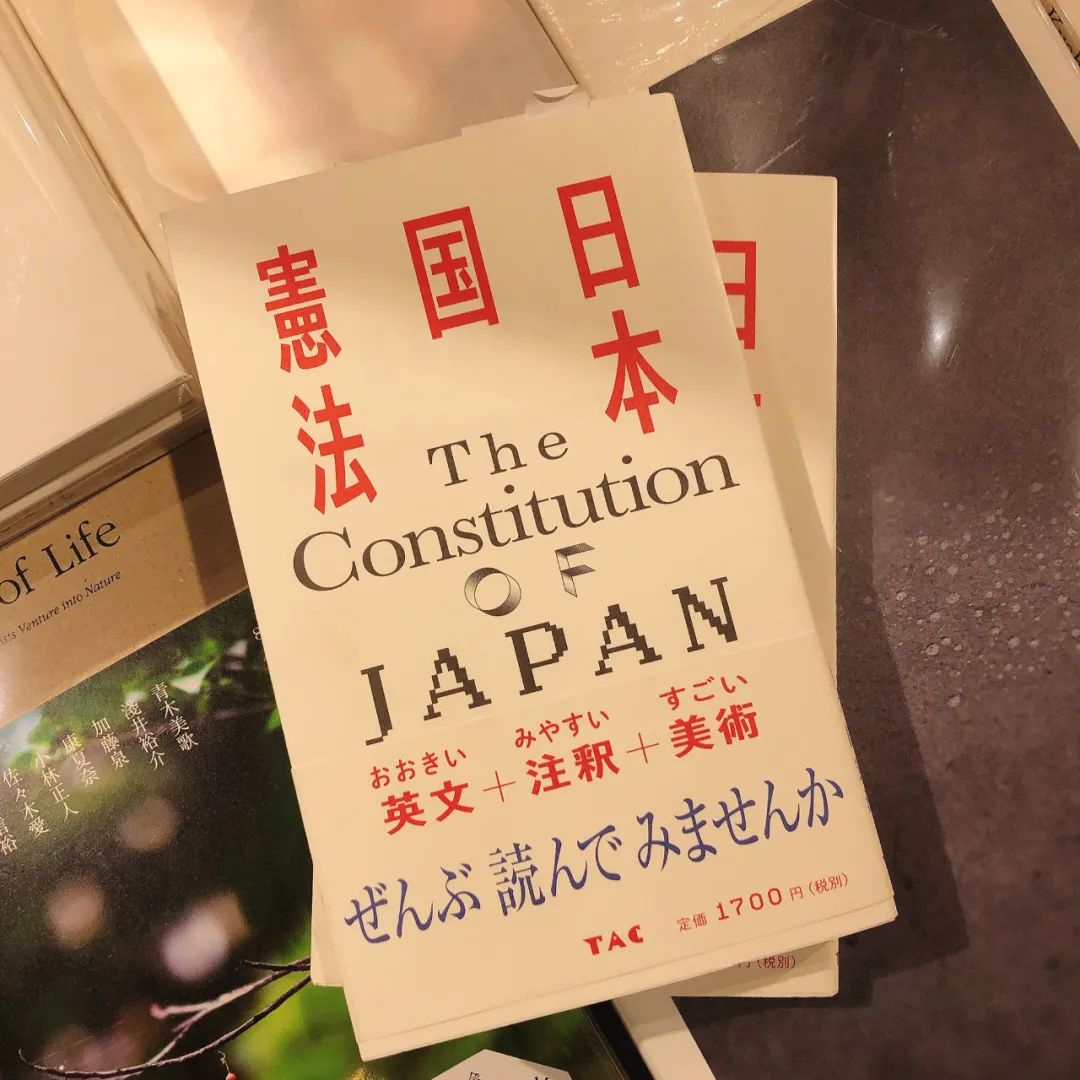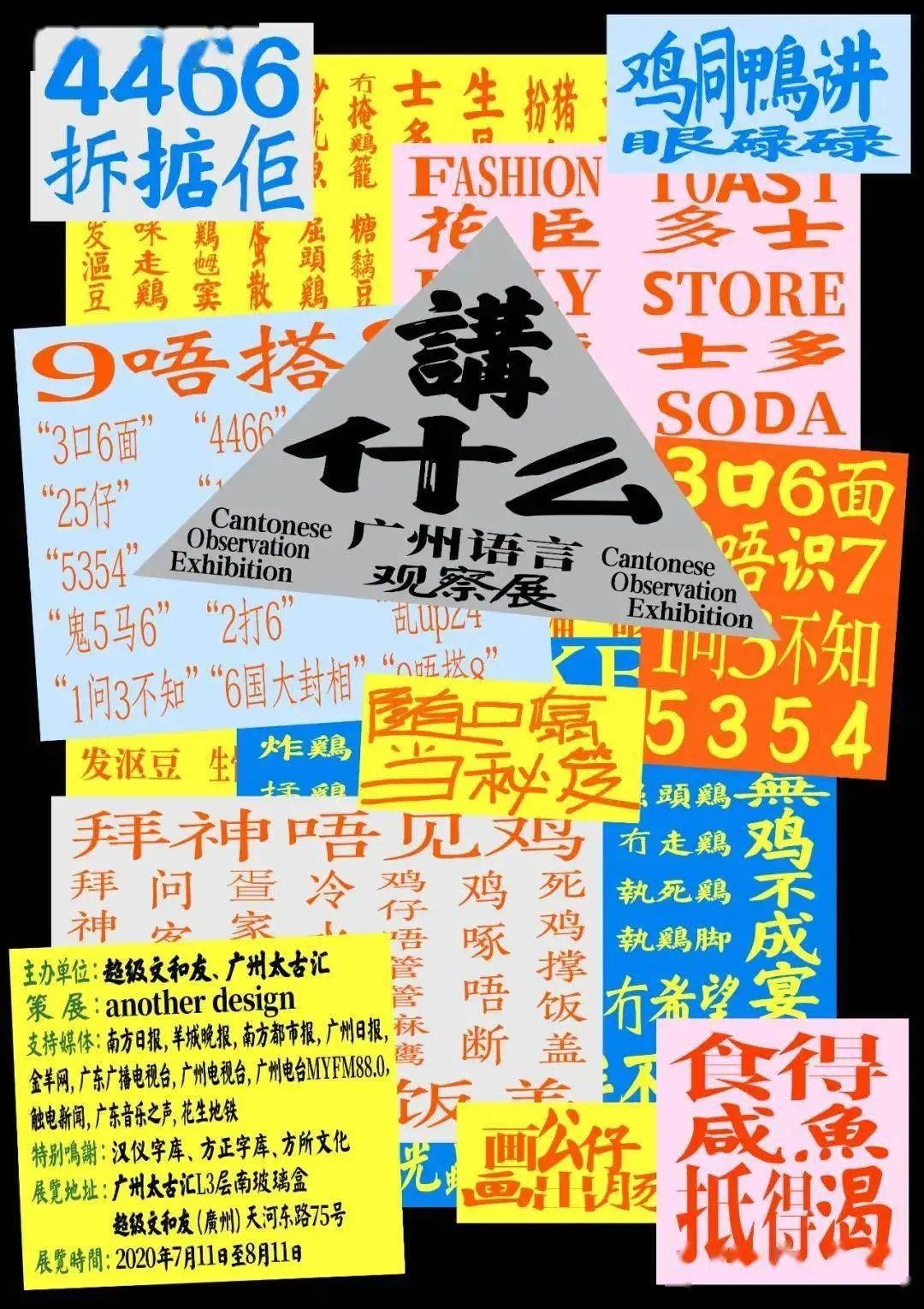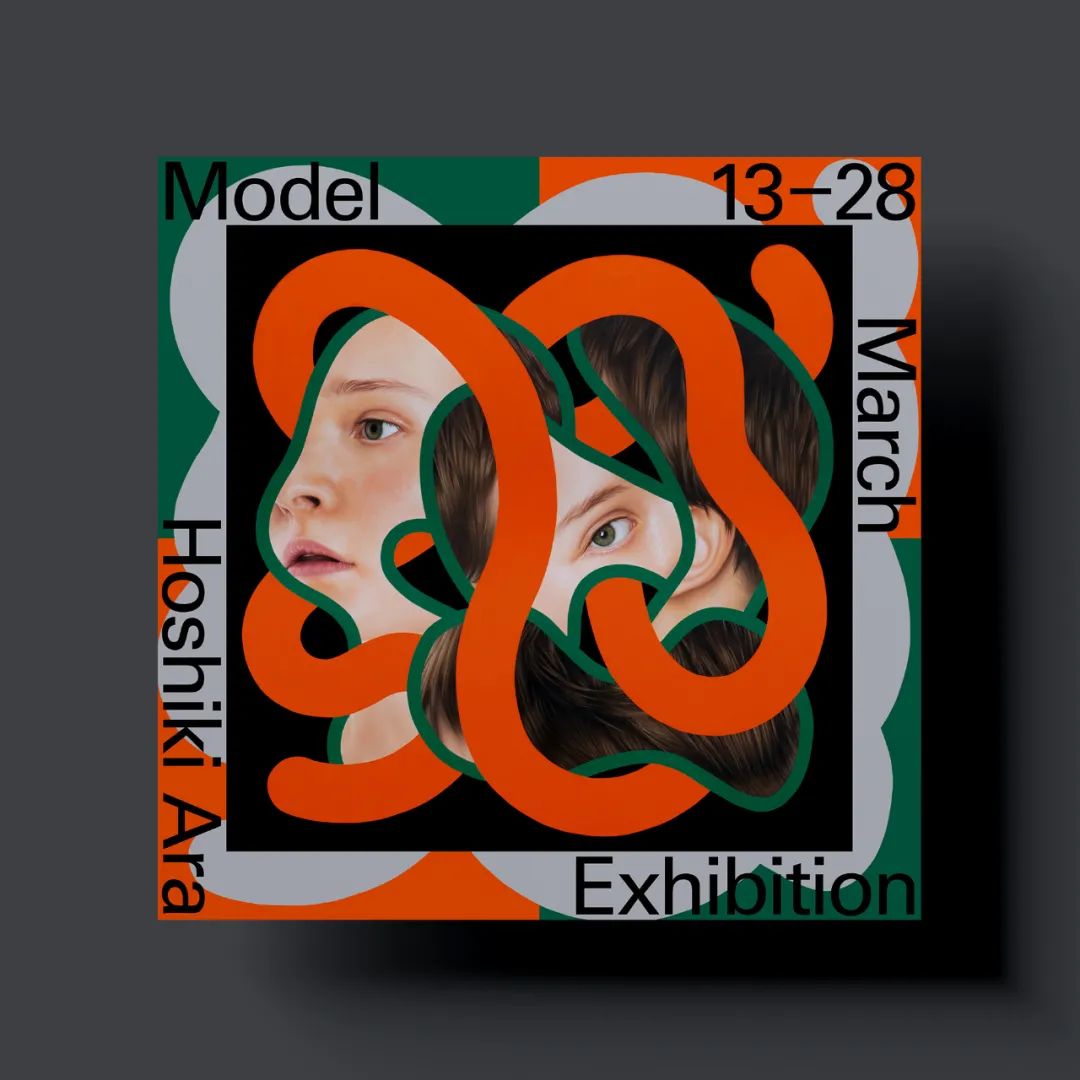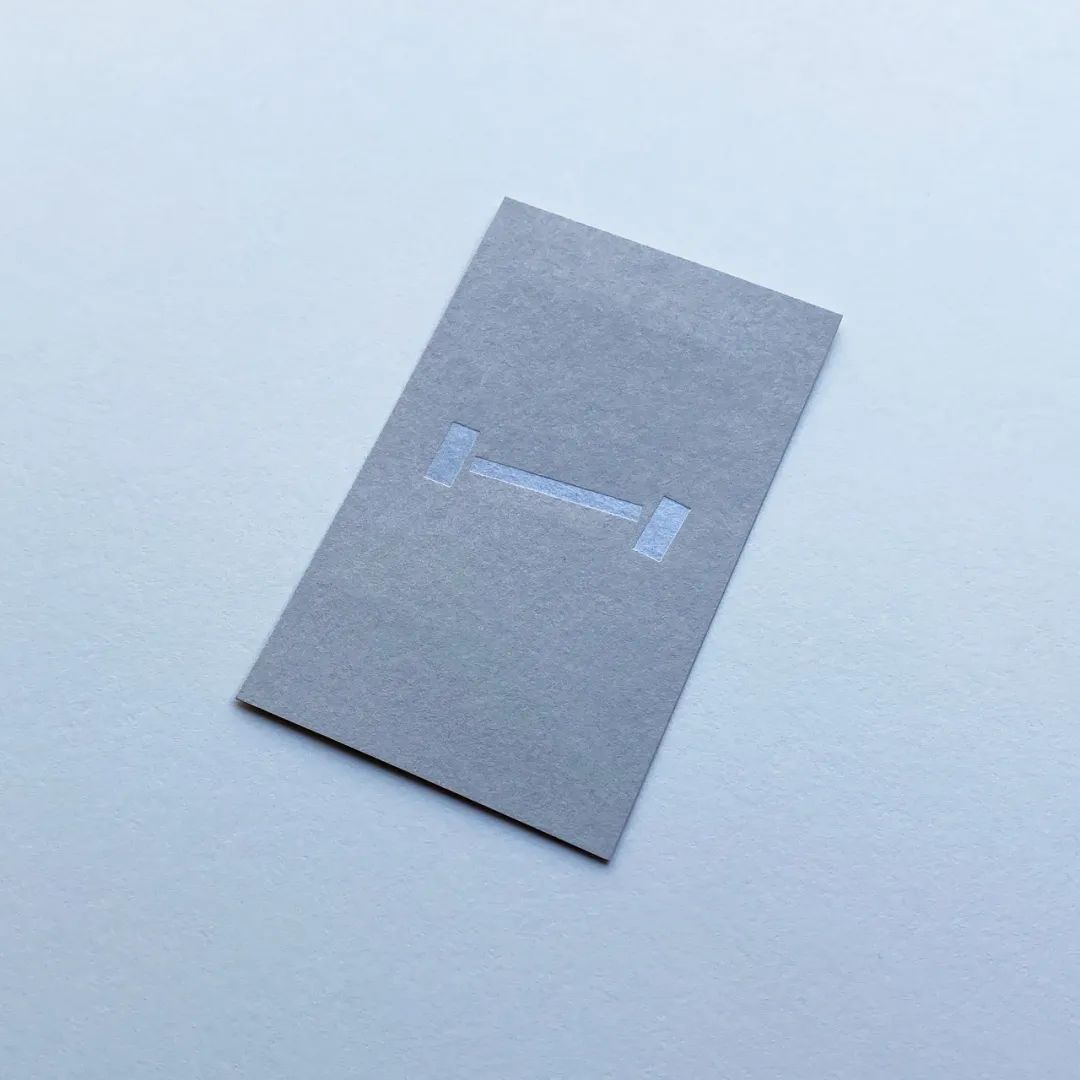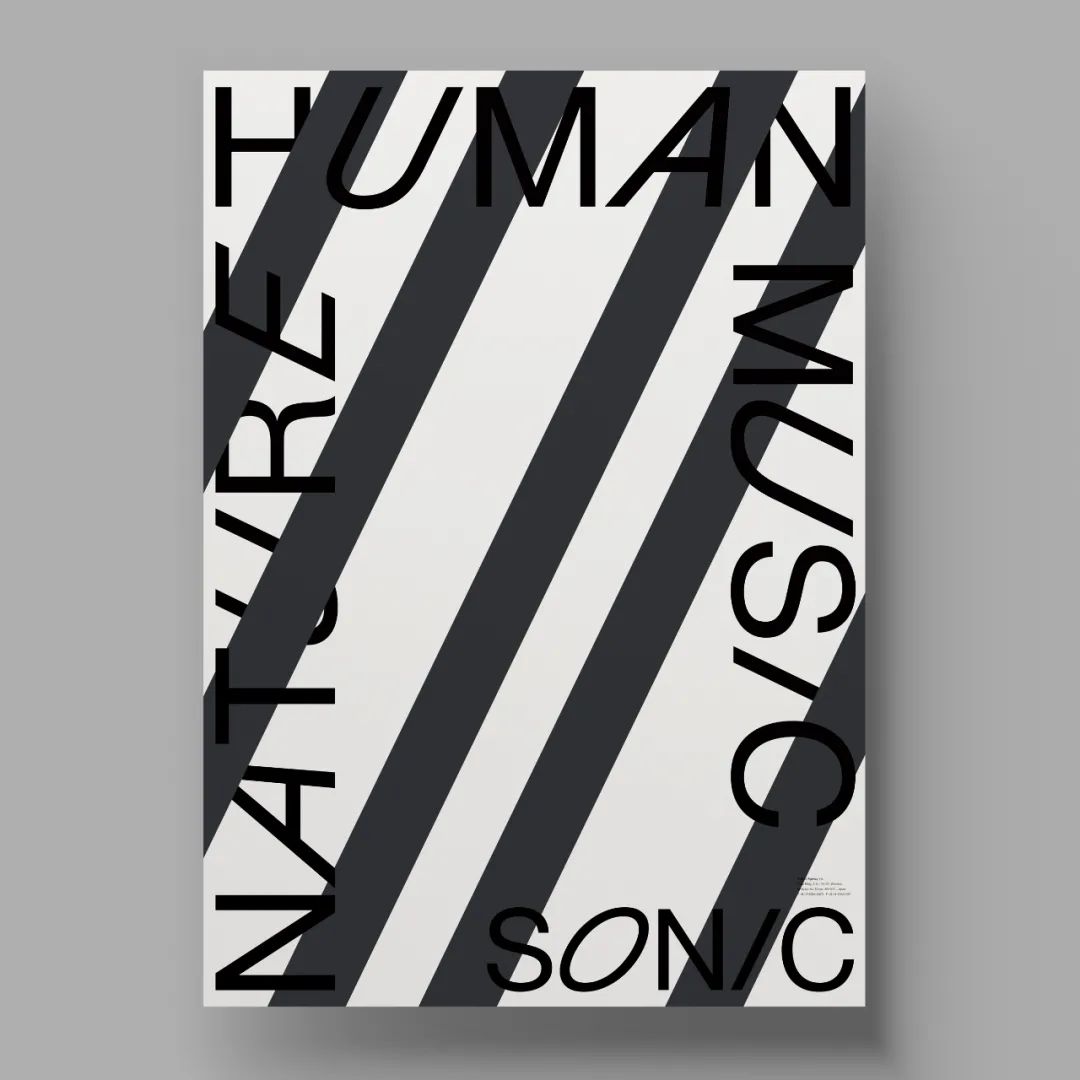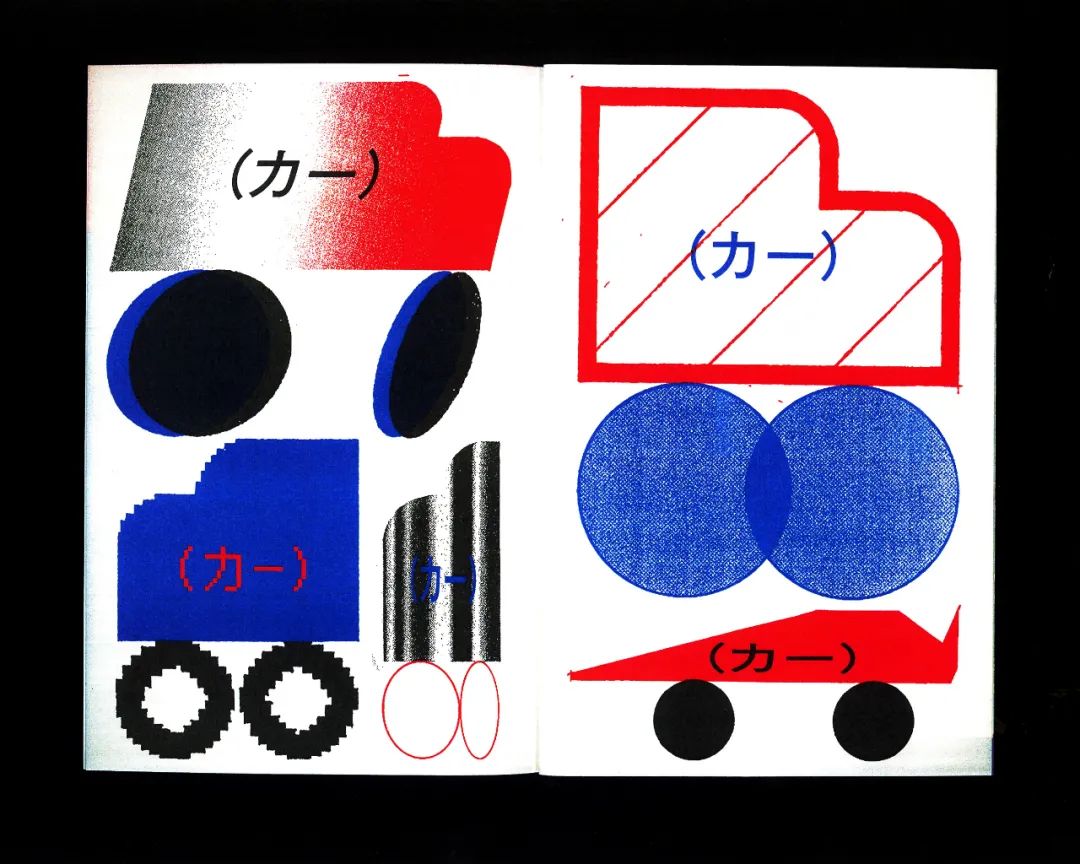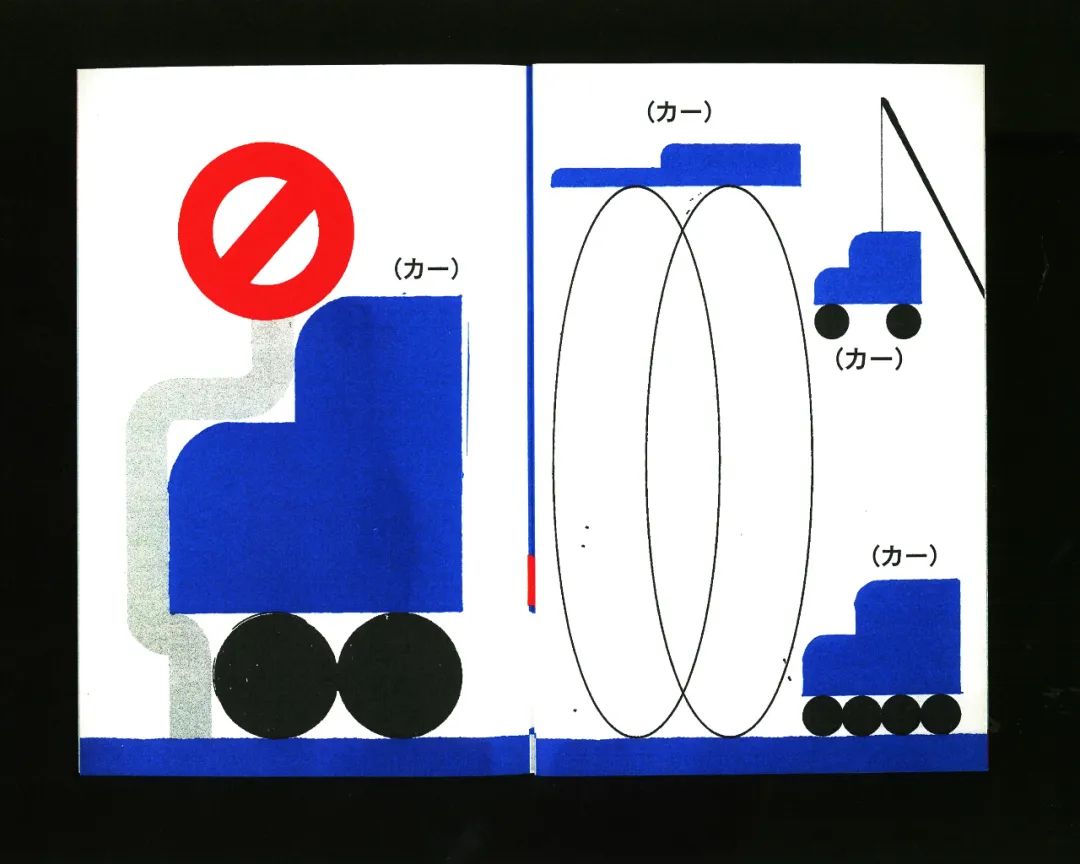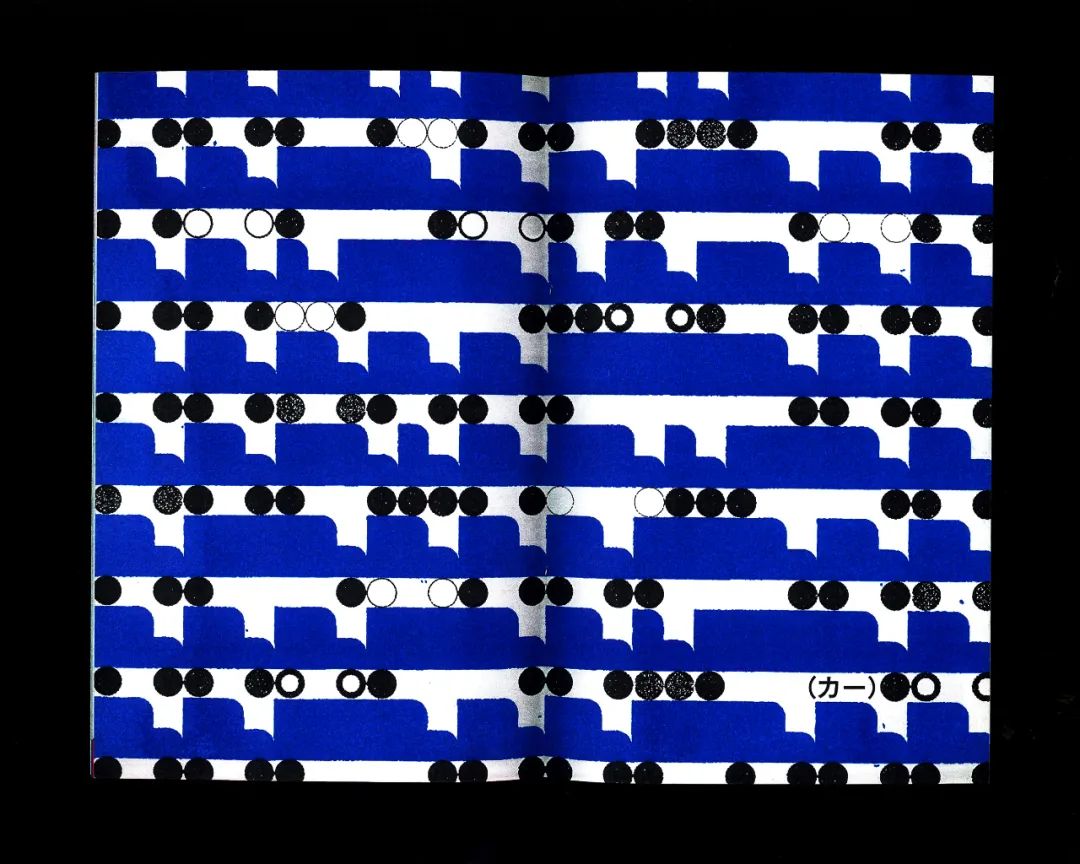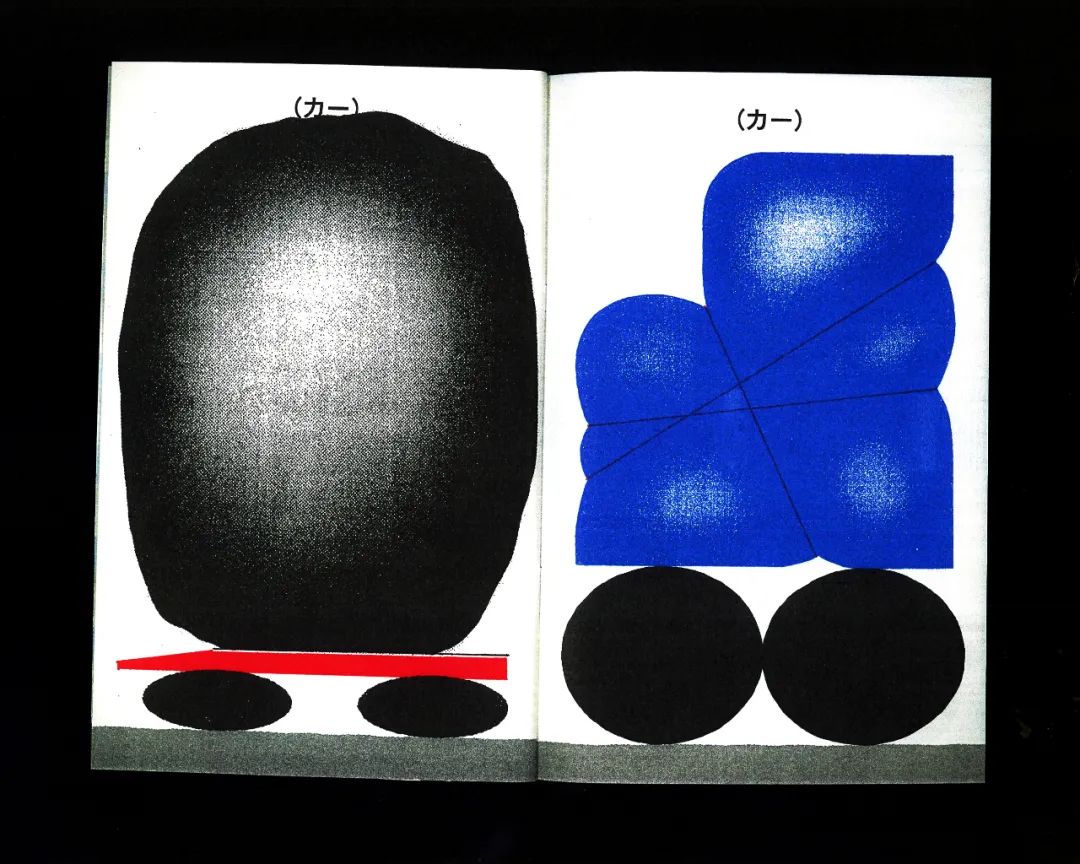
一年一度的東京TDC賞又来啦!
12月25日中午12点,2021东京字体指导俱乐部年度TDC奖公布获奖及提名作品。今年东京TDC组委会考虑到疫情带来的影响,全部采用在线方式收集提交的参赛作品,再由28位评委在线评选出获奖作品。
※ 共收到3750份作品(日本国内1947份、海外1803份),并评选出 12件获奖作品
※ 除了大奖赛以外,其他奖项都是同一级别的奖项
※ 入选作品将于2021年1月中旬通过邮件告知
接下来,和大家简单介绍一下 Tokyo TDC。
Tokyo TDC(东京字体指导俱乐部)始创于1987年,1990年开始设立 東京TDC賞(TDC Annual Awards / 东京字体指导俱乐部奖),2006年被日本东京都政府授予非营利组织(NPO)地位。Tokyo TDC 旨在关注与推崇表现文字和语言之间具有深刻关联的字体设计,同时也十分关注艺术指导者在企业品牌诉求时的品味和视觉沟通艺术及设计的主张。Tokyo TDC 年赛每年从世界各地募集优异的参赛作品,从中选拔出顶尖之作授予 Tokyo TDC 大奖。
本届获奖作品包括全场大奖1名、TDC奖6名、字体设计奖1名、书籍设计奖1名、RGB奖1名、特别奖1名,其中有两件中国作品入选。
OK-RM (Oliver Knight and Rory McGrath) [UK]标题: Gabriel Kuri: Sorted, Resorted客户: Wiels, Brussels (publisher: Wiels and Koenig Books)客户: Coca-Cola China 可口可乐中国标题: TRANS BOOKS DOWNLOADs标题: X-Mas特辑:用饰条和家具印刷——Dafi Kühne 印刷展™
标题: CalorieMate to ProgrammerHenrik Kubel + Scott Williams [UK]Liu Zhao + Zhan Huode + Weng Donghua [中国]客户: Chaoji Wen He You 超级文和友标题: 佐賀町エキジビット・スペース 1983‒2000– TD: Han Gao / Title: Bathroom Paper / CL: Bathroom Store (Category 1)– TD: Lobbin Liu / Title: Occurred during 1 am to 6 am / CL: Non-Commercial Work (Category 1)– TD: ShumWW&yuchenghsiao / Title: 2020 Calendar / CL: Non-Commercial Work (Category 1)– TD: Jason Wolfe & Luke Hall / Title: Beyond Bauhaus: Modernism in Britain 1933‒66 / CL: Royal Institute of British Architects (RIBA) (Category 1)– TD: Kjell Ekhorn & Jon Forss, Non-Format/ANTI / Title: Black Devil Disco Club ‒ Lucifer Is A Flower / CL: Lo Recordings (Category 1)– TD: Lucas Machado / Title: Dsgnselo Catalogue 2020 / CL: Dsgnselo (Category 1)– TD: 加瀬 透 / Title: 都市計画 (Urban Planning) / CL: (株)スペースシャワーネットワーク (Category 1)– TD: 加瀬 透 / Title: Taiko Super Kicks SOLO SHOW “talkback” / CL: Taiko Super Kicks (Category 1)– TD: 髙田 唯 / Title: Festival/Tokyo DM・フライヤー・タブロイド・オンライン会場ビジュアル・ポスター / CL: Festival/Tokyo (Category 1 + 7)– TD: 葛西 薫 / Title: ミナ ペルホネン/皆川明 つづく / CL: 東京都現代美術館 (Category 1 + 7)– TD: 葛西 薫 / Title: A&S AOYAMA / CL: ARTS&SCIENCE (Category 1)– TD: 植原亮輔、渡邉良重 / Title: 祝いと酔独楽 / CL: OFS Gallery (Category 1 + 7)– TD: 小杉幸一 / Title: YMO40 / CL: (株)ソニー・ミュージックエンタテインメント (Category 1)– TD: 石塚 俊 / Title: Echo after Echo:仮の声、新しい影 / CL: 東京都現代美術館 (Category 1 + 7)– TD: OK-RM (Oliver Knight and Rory McGrath) / Title: The Inflatable Archive / CL: Moncler (Category 2)– TD: Fraser Muggeridge / Title: Period / CL: Fiona Banner (Category 2)– TD: Yang Keyi / Title: 象の話——魯迅のデザイン作品における視覚言語の探求 / CL: 2019 武蔵野美術大学修了製作 (Category 2)– TD: Fiete Stoll / Title: Mercator Foundation Annual Report / CL: Stiftung Mercator (Category 2)– TD: WeiQun,Cai / Title: XIU-This book can be weaving / CL: Taiwanese (Category 2)– TD: Kellenberger–White / Title: In Formation / CL: White Cube (Category 2)– TD: Wujun Miao / Title: On the road to say goodbye / CL: Wujun Miao (Category 2)– TD: 松永美春 / Title: SS19 / CL: Nelly Rodi Japan (Category 2)– TD: 鈴木哲生 / Title: イリュミナシオン ランボオ詩集 / CL: 土曜社 (Category 2)– TD: 佐々木俊 / Title: 「NATURE IS NOT YOUR HOUSEHOLD」ポスター / CL: グレゴリー・アンボス (Category 7)– TD: 服部一成 / Title: Thank You Memory / CL: 弘前れんが倉庫美術館 (Category 7)– TD: 服部一成 / Title: HOSE 1, 2 / CL: ALT SPACE LOOP, SEOUL (Category 7)– TD: 田部井美奈 / Title: 武蔵野美術大学 イメージビジュアル / CL: 武蔵野美術大学 (Category 7)– TD: 菊地敦己 / Title: 菊地敦己2020 / CL: (株)リクルートホールディングス (Category 7)– TD: 石塚 俊 / Title: 植物の生の哲学 / CL: グレゴリー・アンボス (Category 7)– TD: Jonas Zieher, Tony Brook / Title: Spin Projects +/‒ / CL: Non-Commercial Work (Category 8)– TD: Xiaoqun Wu & Oliver Hischier / Title: Silk Pagodas / CL: Self initiated project (Category 8)– TD: Zhuohan Shao / Title: Write from memory about Hangzhou / CL: Non-Commercial work (Category 8)– TD: OK-RM / Title: ‘Show in a box’ JW Anderson, MS21 and WRS21 / CL: JW Anderson (Category 8)– TD: M/M (Paris) / Title: M/Made in Shanghai / CL: Power Station of Art (Category 8)– TD: Kellenberger–White / Title: Metal Type / CL: V&A Dundee / self-initiated (Category 8)– TD: Martin Grasser / Title: Color Dot Font / CL: Non-Commercial Work (Category 8)– TD: Kellenberger–White / Title: Carmody Groarke Website / CL: Carmody Groarke (Category 9)– TD: 萩原俊矢 / Title: TRANS BOOKS Website Series / CL: TRANS BOOKS (Category 9)– TD: 田中良治 / Title: JAGDA, The Graphic Design Review ウェブサイト / CL: 公益社団法人日本グラフィックデザイナー協会 (Category 9)– TD: Youting Lin / Title: A BIG CRUSH / CL: School of Visual ArtVideo (Category 10)– TD: Aaron Nieh / Title: Sign Switching For Brussels Station / CL: Non-Commercial Work (Category 11)– TD: 石橋友也+新倉健人 / Title: 機械詩の部屋 / CL: Non-Commercial Work (Category 11)
“Model” Hoshiki Ara Exhibition フライヤー
▽ 提名作品
ケイモトシュンスケ
标志设计「IPPO」
2021に自作冊子「SUPER DUPER PAPER DRIVER」FESTIVAL / TOKYO 2020 宣传材料被提名东京TDC奖2021
▽ 提名作品
mei_otsubo
東京TDC賞2021、山本海苔店のカタログ入選
https://tokyotypedirectorsclub.org/news/tdc2021-results/多年来,Tokyo TDC 不断挑战视觉排版的定义与型式、字形和字体的所有关联图形设计,推动字体在印刷、广告(静态/动态)、出版和屏幕的应用与创新,涉及当代字体设计的各个领域。当前 Tokyo TDC 已成为了屈指可数的全球性设计比赛之一。